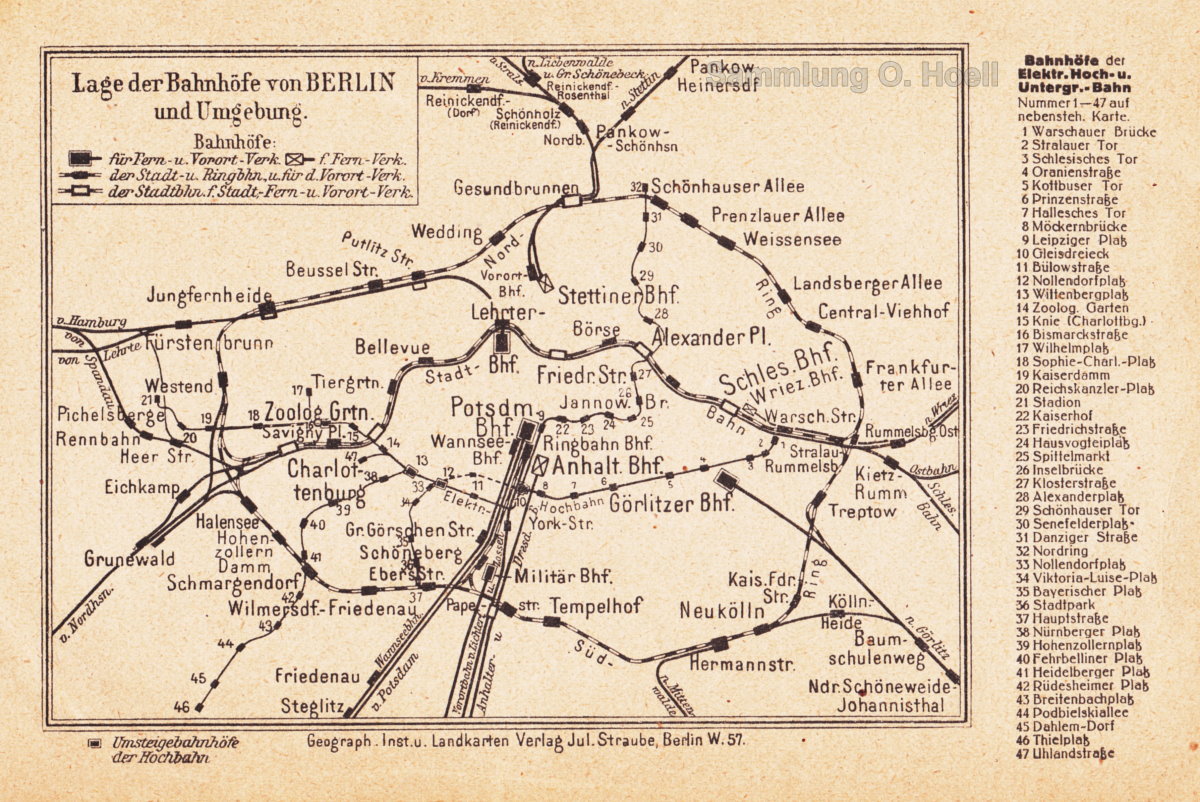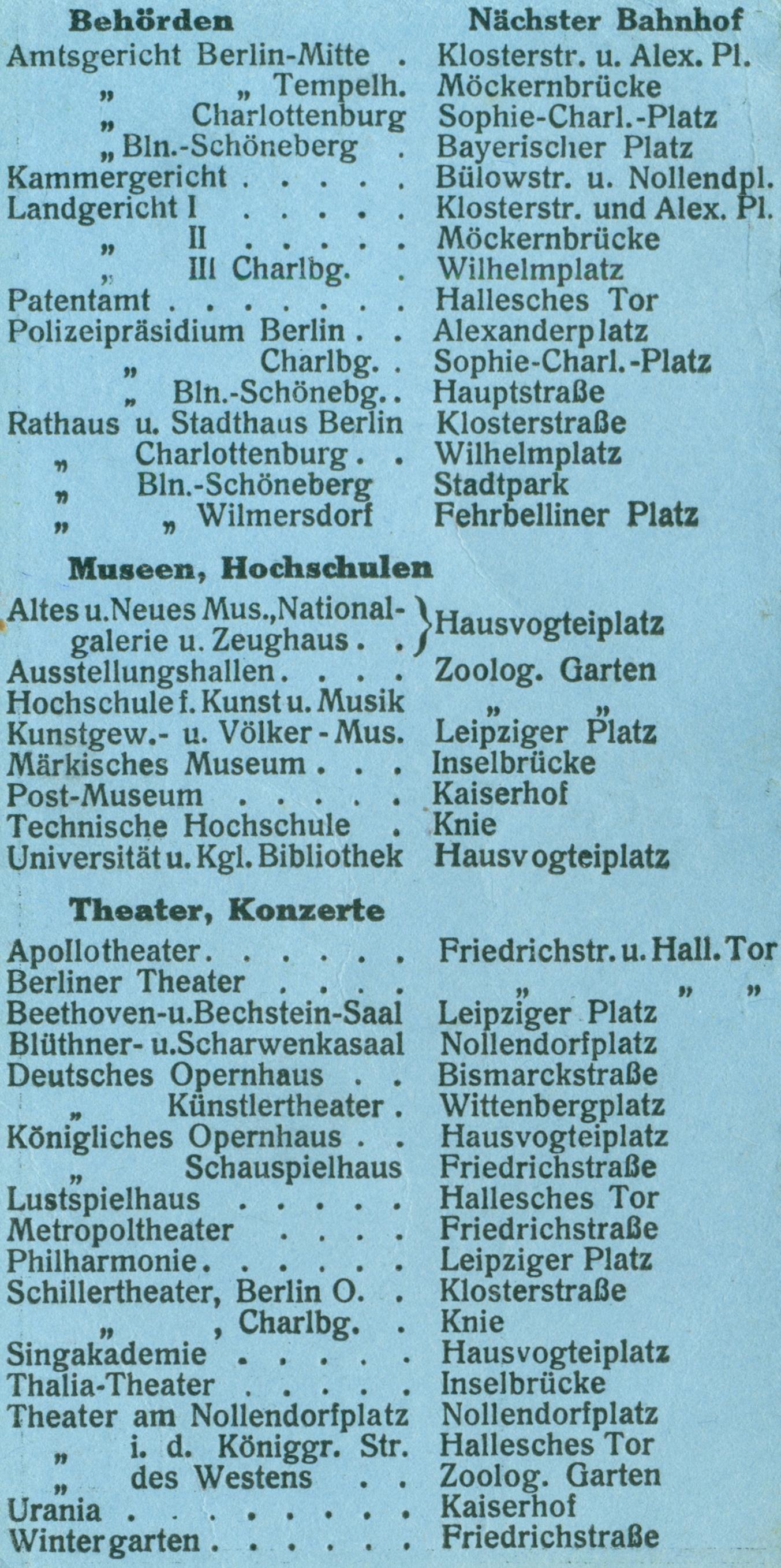
ich bin auf der Suche nach der auf angehängtem Scan zu erkennenden bzw. einer ähnlichen oder zumindest zeitgemäßen Schritart.
So verwendet wurde diese hier auf einem Ende 1913 erschienenen Taschenfaltplan der Berliner U-Bahn.
WhatTheFont schlägt mir eine hebräische vor... :-(
Das H ist sehr markant … vielleicht hilft die Form der tz-Ligatur beim Erkennen?
Jenes aus Alex’ Beitrag:
Das auch in der Aufzählung der Bahnhöhe in meinem Post vorkommt. Die Antiqua dort ist ja identisch mit derjenigen aus Alex’ Bild. Dass das "… wieder eine ganz andere Antiqua …" sei stellt sich für mich nicht dar.
Da hab ich mich wohl vom H blenden lassen und den Rest nicht mehr sorgfältig verglichen ;-) .
Das am besten passende, das ich finden konnte, ist das hier: (aber wohl kaum digitalisiert zu haben58a0567c358b5_ElzevirII.JPG.a82428fb5c6827e8de638aaafa4771ce.JPG:-(
Unterschiede liegen wohl in der unterschiedlichen Entwurfsgröße der Schrift. "Hamburgers" dürfte die 20er zu sein, den Textausschnitt schätze ich auf die Schriftgröße 8 - 10 pt? Die hat dann einen Hauch geringere Kontraste und ist etwas fetter.